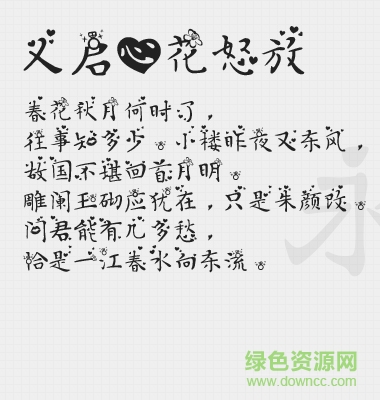
軟件介紹 軟件標(biāo)簽: 義啟字體 字體 義啟心花怒放ttf是一款非常浪漫的字體,該字體自帶星光效果,字庫完整,可應(yīng)用于情人節(jié)設(shè)計方面,喜歡的朋友快來綠色資源網(wǎng)下載收藏吧!義啟心花怒放字體安裝方法方法一:控制面板/字體/文件/安裝新字體;方法二:直接將字體復(fù)制到C:\WINDOWS\Fonts。方法三:針對win7系統(tǒng),用戶只需選中字體右鍵安裝即可。溫馨提示本站所有字體資源僅供個人學(xué)習(xí)與參考,如需商業(yè)使用請到相關(guān)官網(wǎng)授權(quán)! 軟件截圖 上一張下一張(1 / 1) 安裝詳細(xì)截圖 猜你喜歡 花字體 商業(yè)字體 花字體 花朵字體形狀特殊,整體給人非常喜慶的感覺,但好多用戶抱怨找不到合適的花朵字體,特此小編整理了庫里面比較熱門的花字體,提供給廣大網(wǎng)友,希望能滿足大家的藝術(shù)范! 查看更多>> 盛世花開體 6.94M/中文/10.0/下載 移花別戀體 7.61M/中文/10.0/下載 三生三世十里桃花字體 6.27M/中文/4.0/ttf版下載 伯樂花香體 2.06M/中文/10.0/下載 花漾字體ttf 5.42M/中文/10.0/下載 墨染蓮花碎字體 5.85M/中文/10.0/下載 商業(yè)字體 商業(yè)字體是應(yīng)用在商品包裝、平面設(shè)計、影視設(shè)計、雜志報刊、印刷排版等領(lǐng)域的字體,涵蓋了柔美的、古韻的、現(xiàn)代感等不同風(fēng)格的字體,可適用于各種商業(yè)領(lǐng)域! 查看更多>> hiragino sans gb w6字體 10.15M/中文/7.0/下載 hiragino sans gb w3亮體 16.60M/中文/3.8/下載 電腦字體奇思楷體 2.92M/中文/10.0/下載 ubuntu字體合集 1.68M/中文/6.0/下載 universltstd英文字體 23KB/中文/10.0/下載 roboto字體 991KB/中文/10.0/下載 其他版本下載 標(biāo)題 大小 更新日期 下載 義啟簡圓體ttf 1.41M 2018-05-09 下載 義啟橙嘖嘖體 ttf免費版 1.80M 2017-02-13 下載 義啟未來體 免費版 2.92M 2018-03-14 下載 義啟中秋體字體 ttf免費版 3.59M 2018-04-07 下載 義啟月亮體 2.40M 2017-02-15 下載 義啟顏值體字體 2.40M 2017-02-15 下載 義啟春暖花開體 2.16M 2017-03-07 下載 義啟遇見體字體 10.00M 2017-08-16 下載 義啟星空之翼ttf 782KB 2019-03-22 下載 下載地址 電腦版 義啟心花怒放 ttf免費版 點擊報錯 軟件無法下載或下載后無法使用,請點擊報錯,謝謝! 關(guān)閉報錯反饋 請描述您所遇到的錯誤,我們將盡快予以修正,謝謝! *必填項,請輸入內(nèi)容 本類最新 dreamweaver字體庫 首爾南山體字體 v1.06 官方版 潮字社風(fēng)云簡ttf 潮字社凌渡鯤鵬簡體字體 潮字社曾玉波手書簡字體 微博慧心字體 相關(guān)文章 Photoshop字體安裝使用方法和技巧 如何解決“無法新增字體”問題 Win 7系統(tǒng)安裝字體方法 網(wǎng)頁字體大小設(shè)置方法 怎么改網(wǎng)頁字體大小 在Linux系統(tǒng)中安裝字體的幾種方法 windows7字體顯示問題:打開某些程序的時候顯示的是亂碼 用戶評論 熱門評論 最新評論 發(fā)表評論 查看所有評論(0) 昵稱: 請不要評論無意義或臟話,我們所有評論會有人工審核. 字?jǐn)?shù): 0/500 (您的評論需要經(jīng)過審核才能顯示)